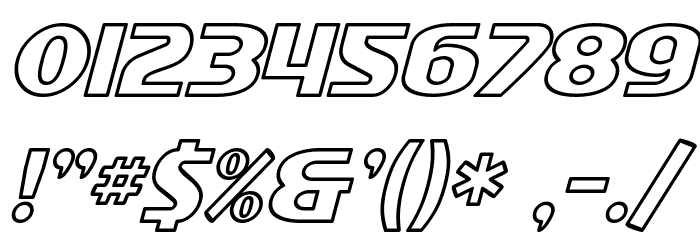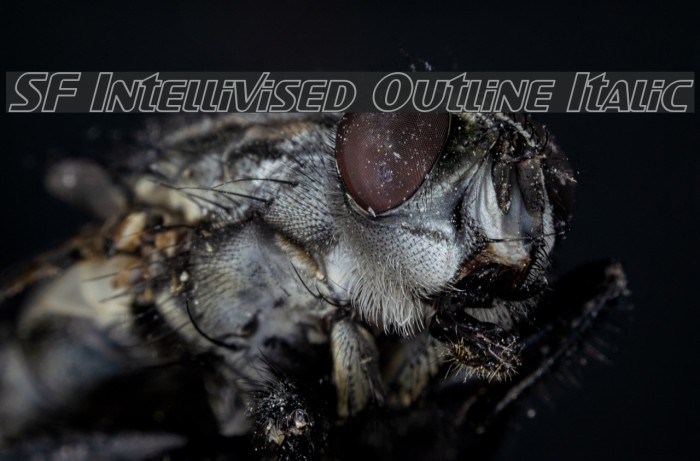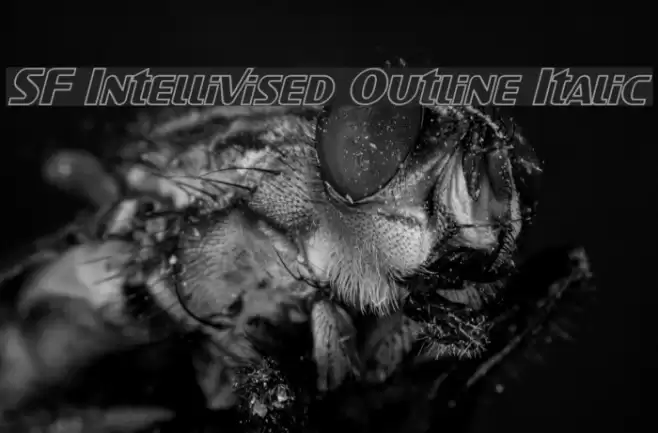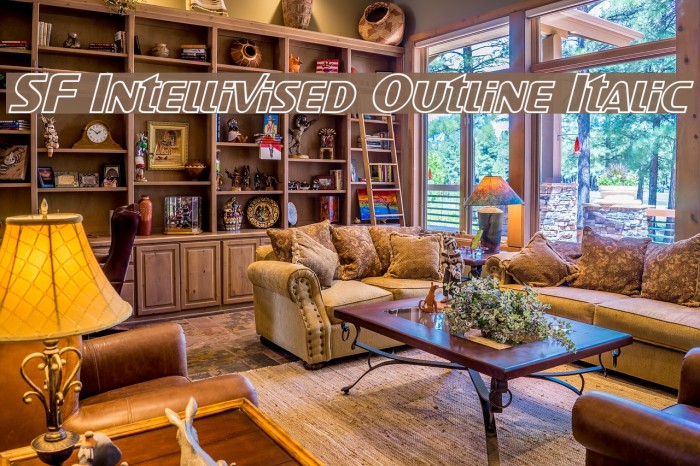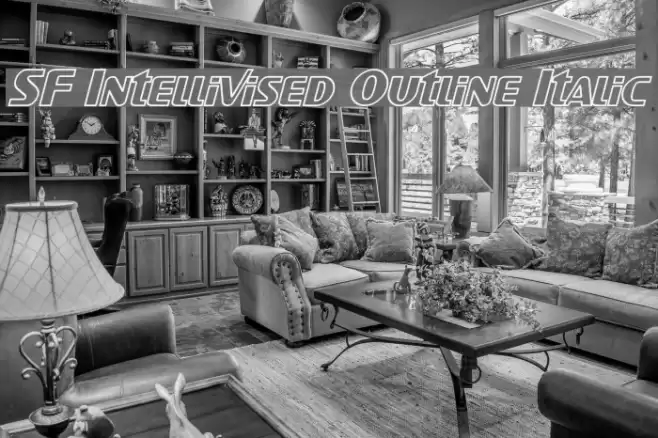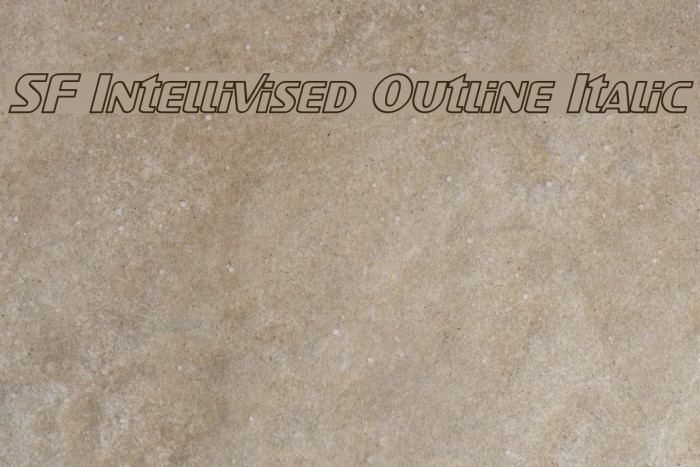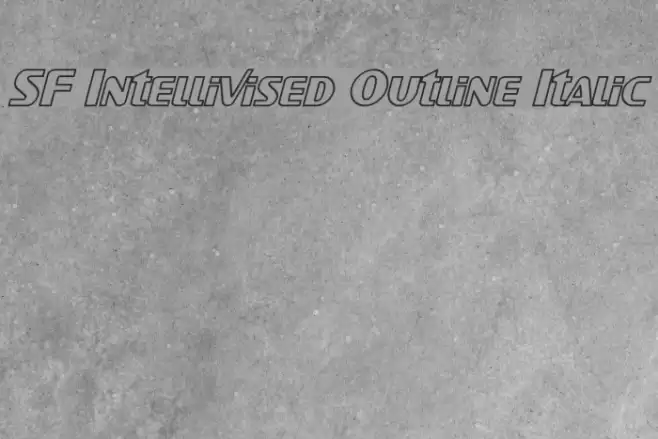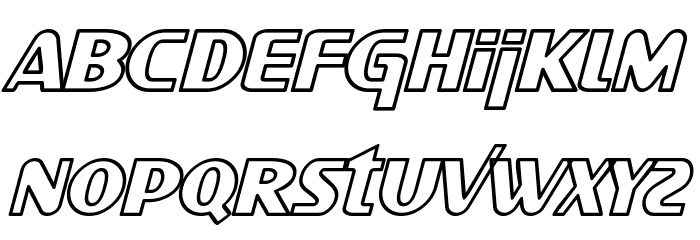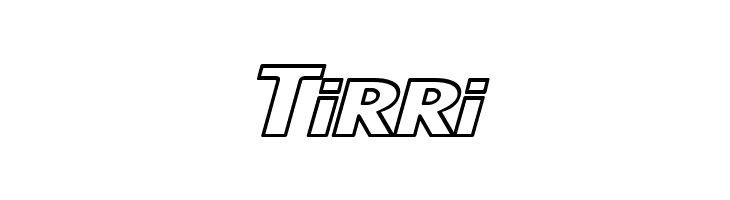
SF Intellivised Outline Italic Font
| Anwendungsfall | Logos, Headlines, Posters |
| Vorgeschlagene Projekte | Ideal for branding, sports team logos, tech company advertisements, and futuristic-themed designs. |